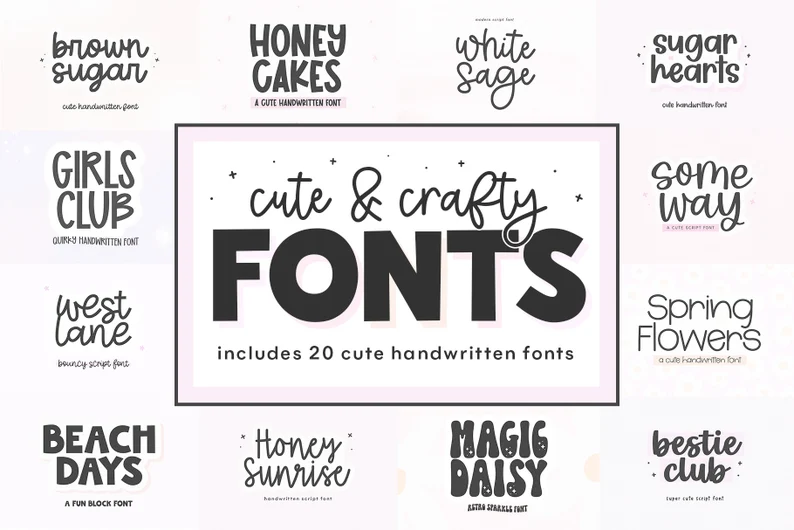
Fonts
في عالم التصميم، يُعد الخط أكثر من مجرد وسيلة لنقل الكلمات، بل هو أداة تعبير بصري تعكس الذوق والأسلوب، وتُكمل الهوية البصرية لأي مشروع. ومن هذا المفهوم جاءت فكرة هذا المنتج الرقمي: “Fonts”، مجموعة خطوط مصممة بعناية لتمنح المصمم أدوات مرنة تساعده على تحويل الأفكار إلى تصاميم تنبض بالشخصية والاحتراف.
تجمع هذه الحزمة بين الجمال البصري والدقة التقنية، لتقدم لك مكتبة خطوط رقمية متكاملة يمكن استخدامها في مختلف أنواع المشاريع الإبداعية، سواء كنت تعمل على شعار جديد، أو تصميم إعلان، أو منشور على وسائل التواصل الاجتماعي، أو حتى مشروع مطبوع مثل كتاب أو غلاف مجلة. تم اختيار الخطوط بعناية فائقة لتغطية أنماط متعددة، من الخطوط الكلاسيكية الأنيقة إلى الخطوط العصرية الجريئة، مع مراعاة التوازن بين الجاذبية البصرية والقراءة السلسة.
إذا كنت مصممًا محترفًا، أو مبتدئًا يسعى للارتقاء بمستواه، أو حتى صاحب مشروع يبحث عن طريقة لتعزيز الهوية البصرية لعلامته التجارية، فإن مكتبة Fonts ستكون استثمارًا حقيقيًا في جودة عملك. هي ليست مجرد مجموعة من الخطوط، بل هي أداة إبداعية متكاملة صُممت لتمنحك الثقة في كل تصميم تقدمه، ولتساعدك على بناء لغة بصرية تنطق بالجمال والتميّز.